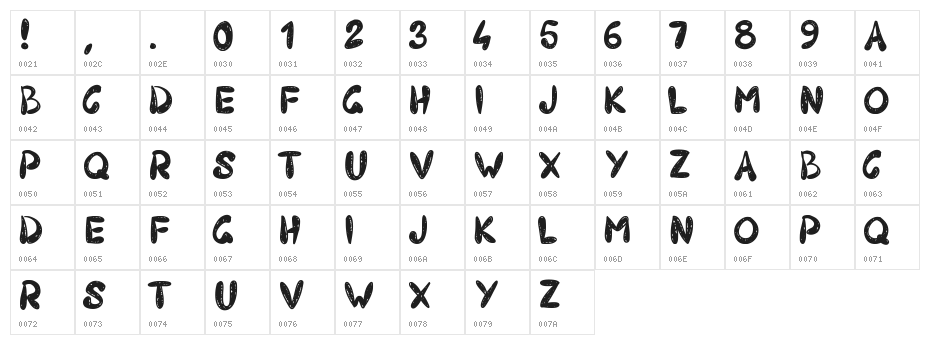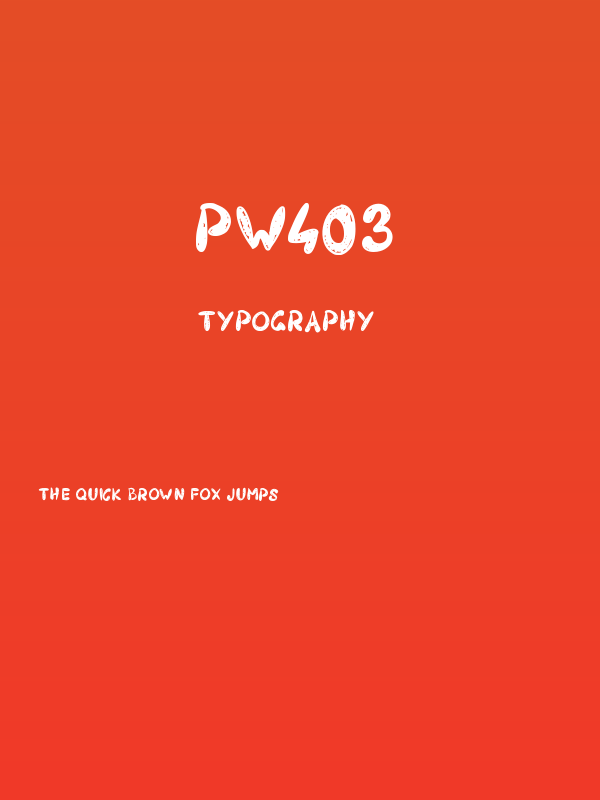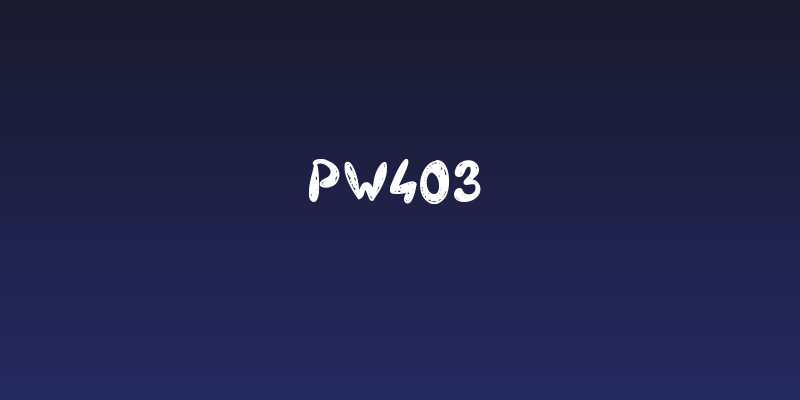
PW403 Font
✎ Cartoon
| Categorie | Cartoon |
| Stile generale | Playful, Whimsical |
| Progetti proposti | Ideal for children's books, playful branding, party invitations, and creative posters. |